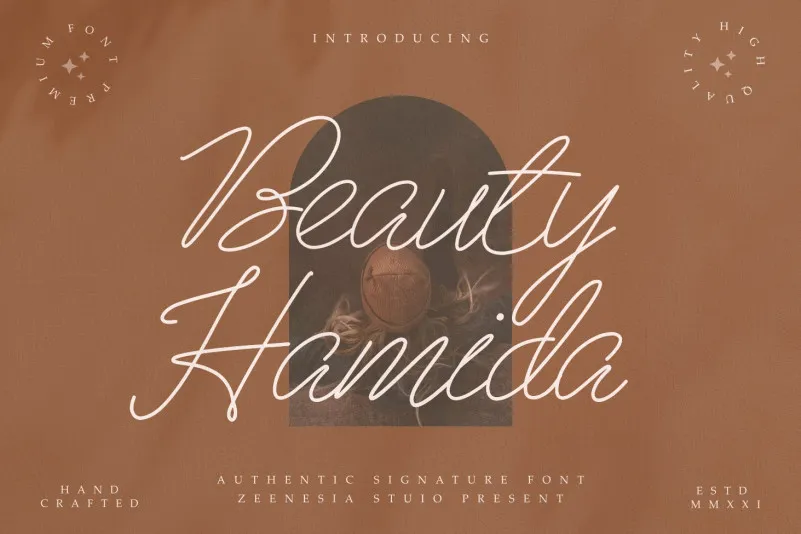
Beau Hamida Font – Download Grátis
Esta é outra deliciosa nova fonte moderna com traço mono, que combina a estética de uma assinatura clássica com um estilo moderno. Esta fonte está equipada para atender a uma ampla variedade de designs devido à sua versatilidade, e tem o potencial de se tornar seu próximo favorito. É ideal tanto para eventos formais quanto para situações mais informais. Se você é fã de linhas retas e textos com estilo único, certamente vai amar a Beau Hamida Font. Esta fonte será um recurso valioso no seu arsenal gráfico.